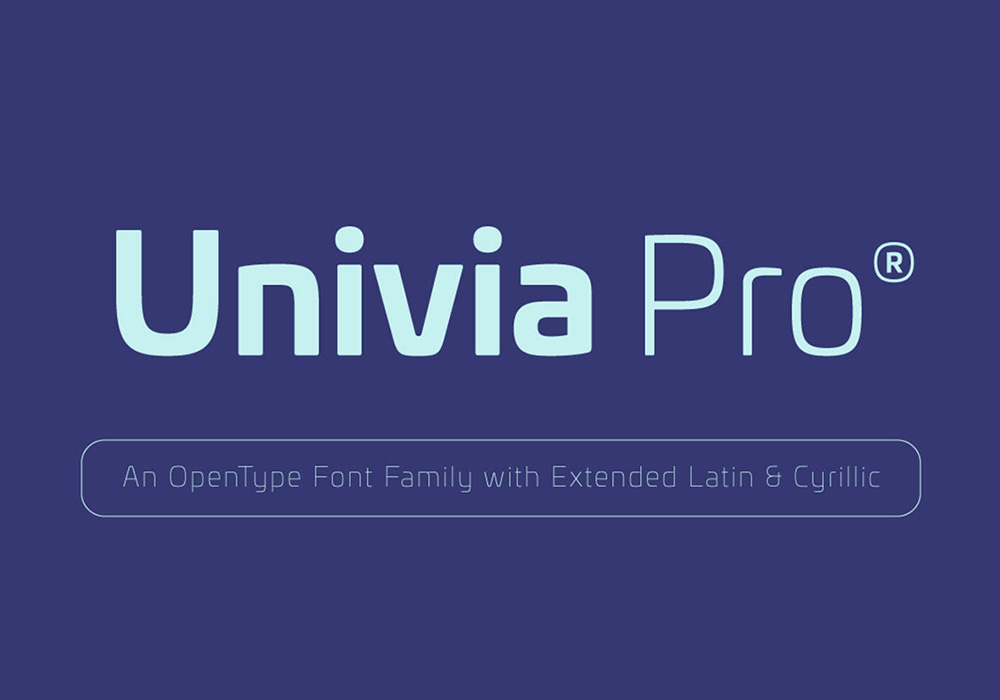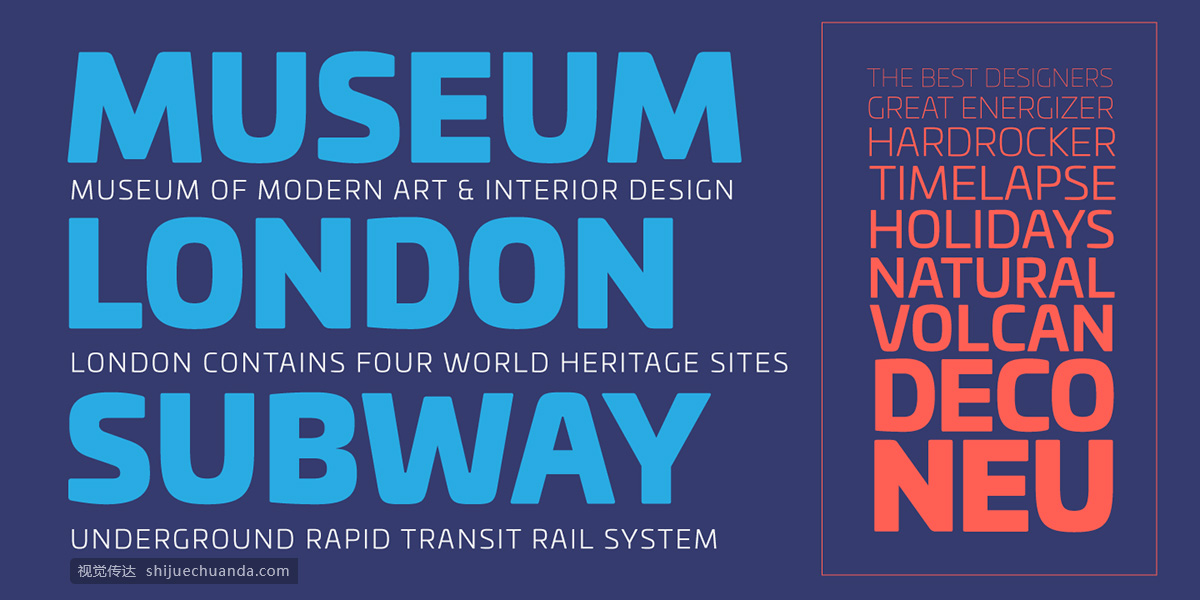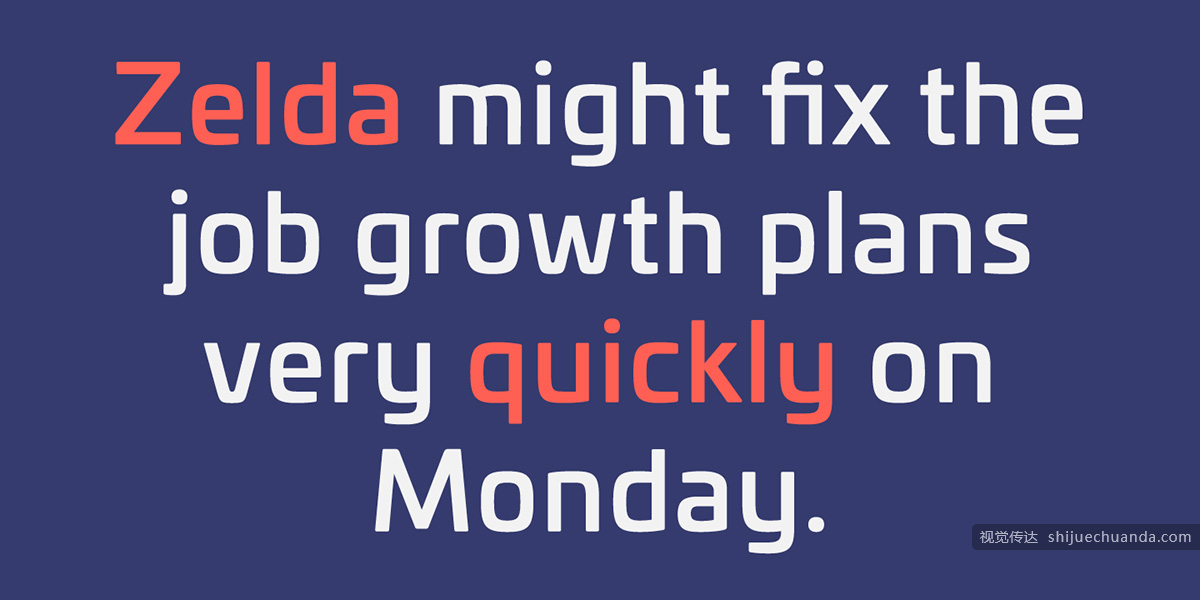
此字体系列 Univia Pro由Olivier Gourvat于2015年12月设计,是一个兼具现代性和多功能性的新型当代OpenType字体系列。具有令人愉悦的外观和极富现代感,与众不同,主要是通过光滑的曲线和圆角实现了个性,这形成了整个家庭的风格。非常适合显示和文本使用,并且由于其超现代的外观,因此非常适合电子书,网站,用户界面字体,移动应用程序等。Univia Pro字体家族中大量配备了OpenType特点:区分大小写,科学上级和下级,标准连字,旧样式,衬砌图形,比例和表格图形,斜杠零,样式集。它还提供了广泛的语言支持。